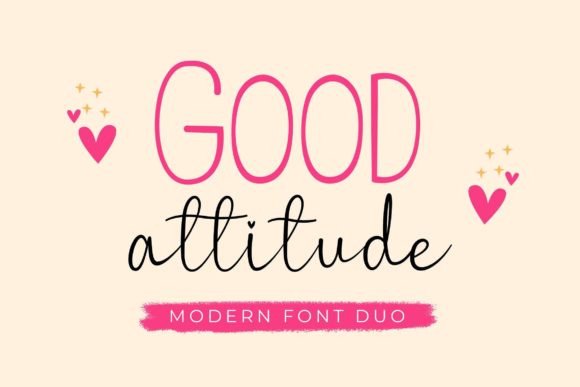
Good Attitude
Encontrar los elementos de diseño adecuados puede ser un desafío, pero Good Attitude ofrece una colección excepcional que eleva tu trabajo al instante.
Elaborado con precisión, Good Attitude proporciona vectores limpios, tipografía suave y una licencia comercial para tu tranquilidad.
Ya sea que estés creando productos POD (impresión bajo demanda), invitaciones de boda o gráficos para redes sociales, Good Attitude es una opción ideal.